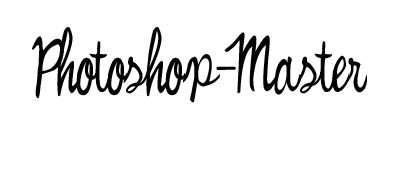
Всеьма-весьма!
спасибо большое.Шрифт супер=)
Сугойный шрифт. На прописной похож
действительно красивый шрифт
Супер шрифт!!!!!!!!!!!!Мне такие всякие разные нравятся!!!!!!!!!!!!!!На подобие этого!!!!!!!!
то что надо...)!!!
Супер,спасибо!!!как раз для приглащения...